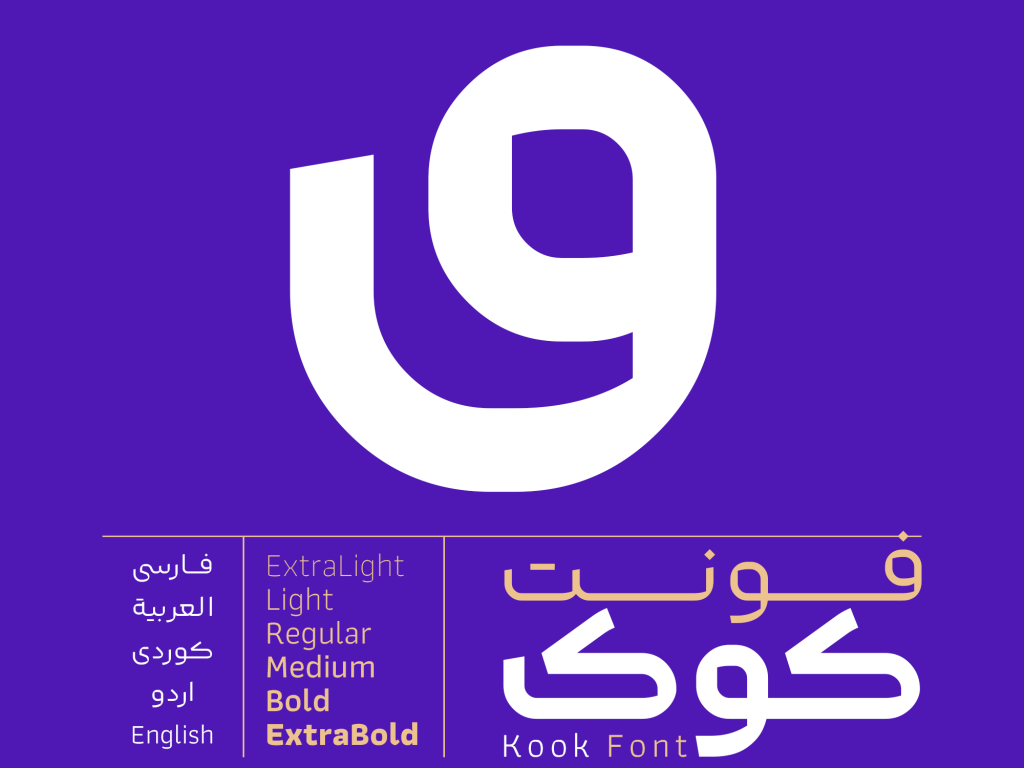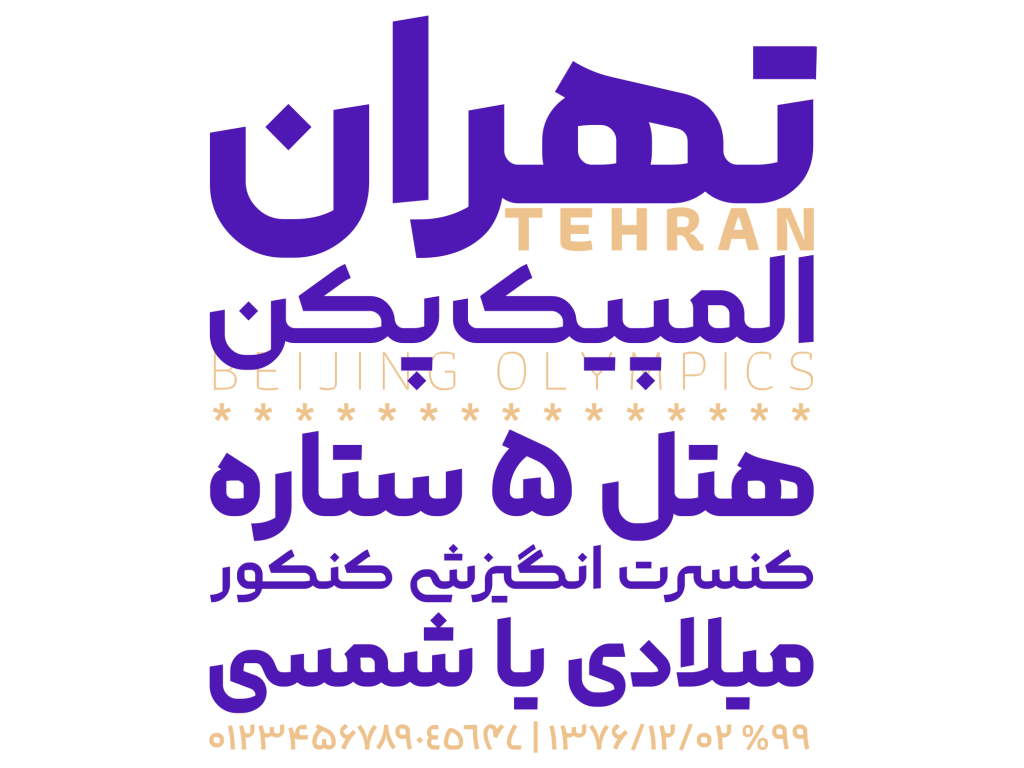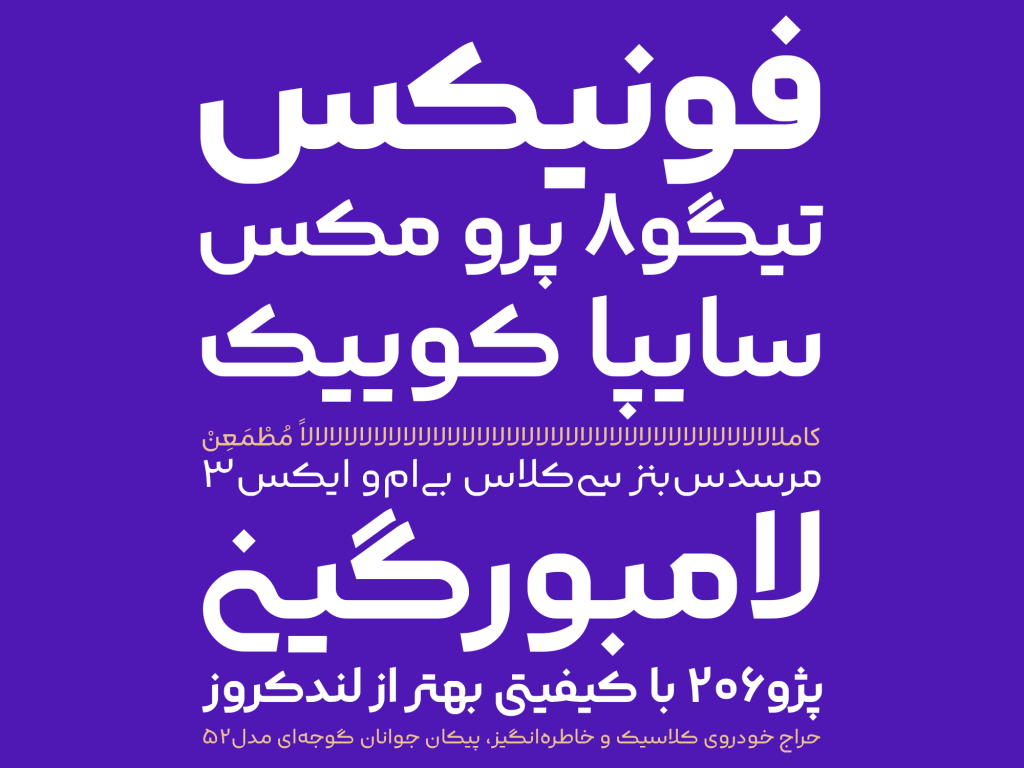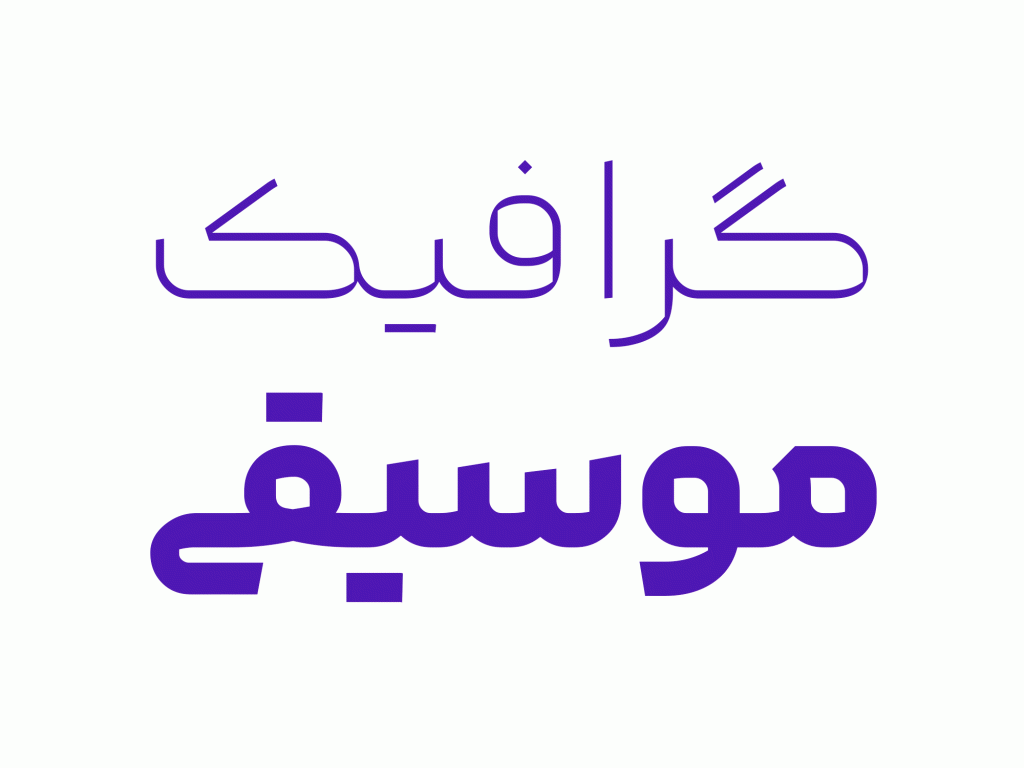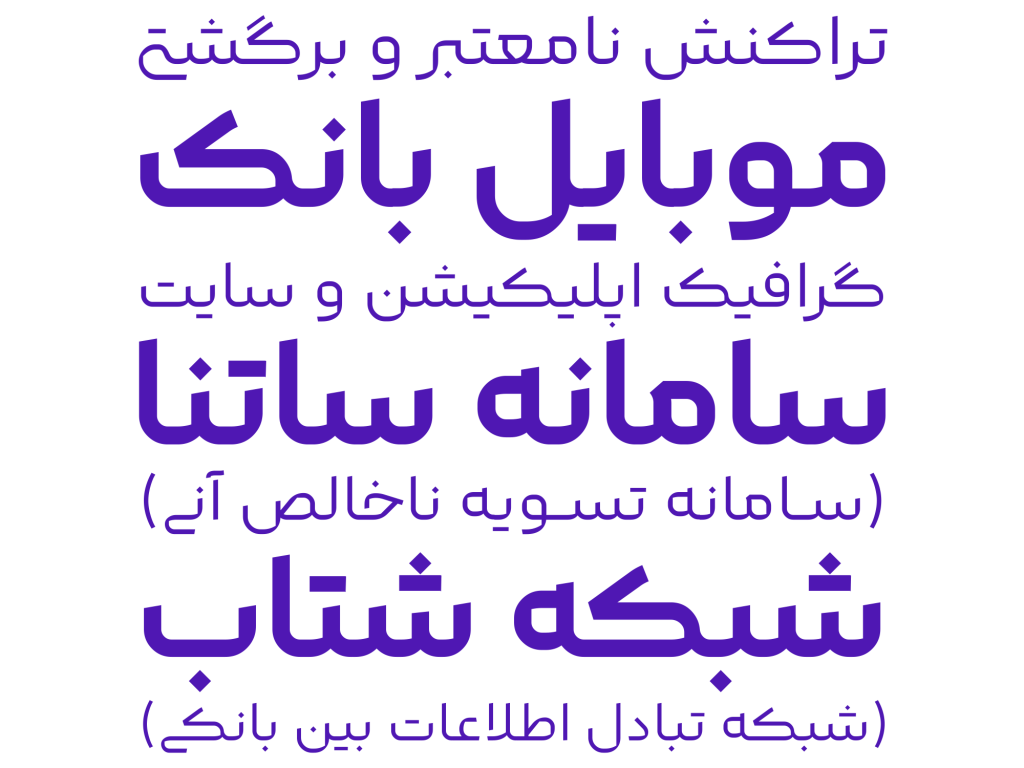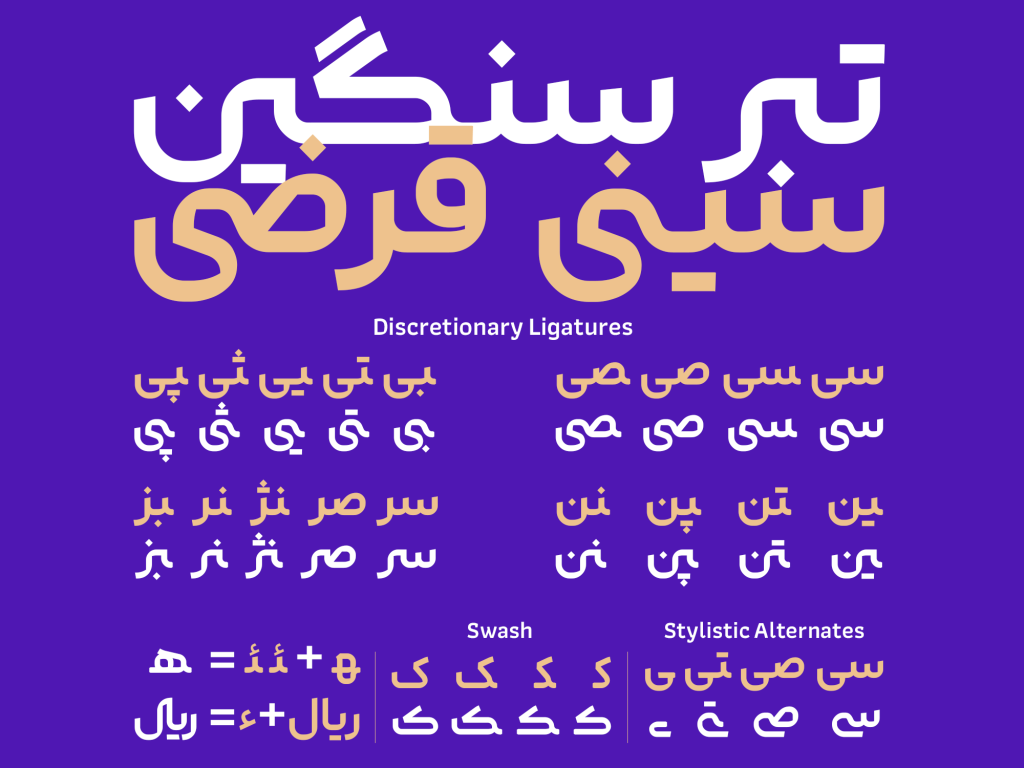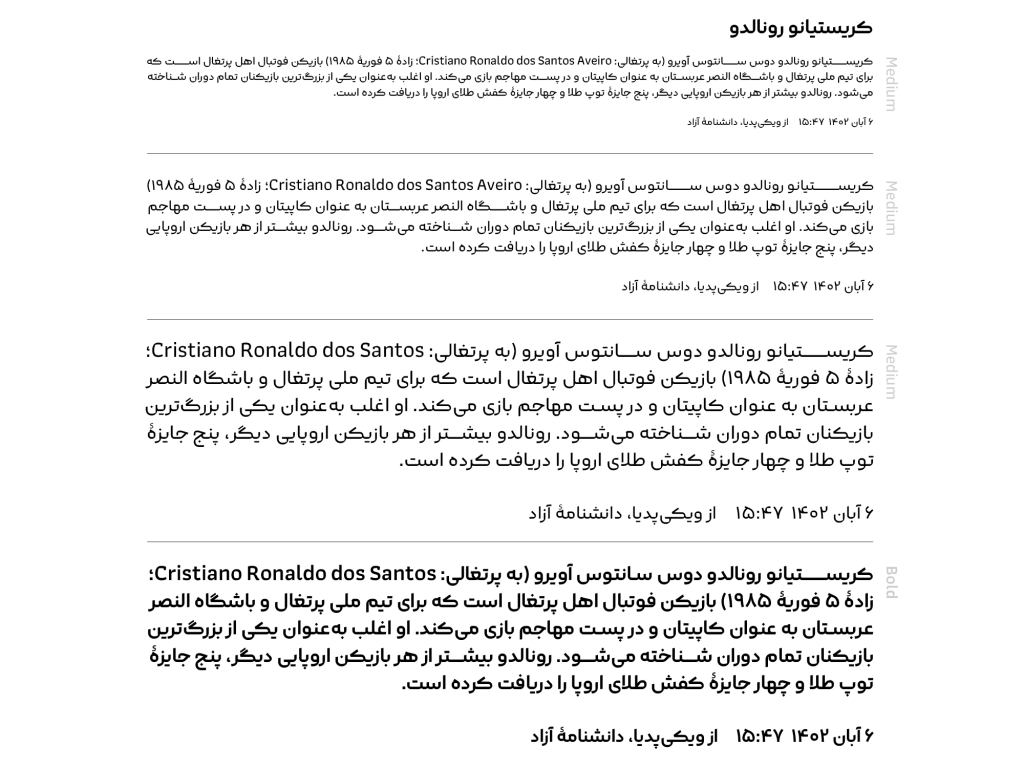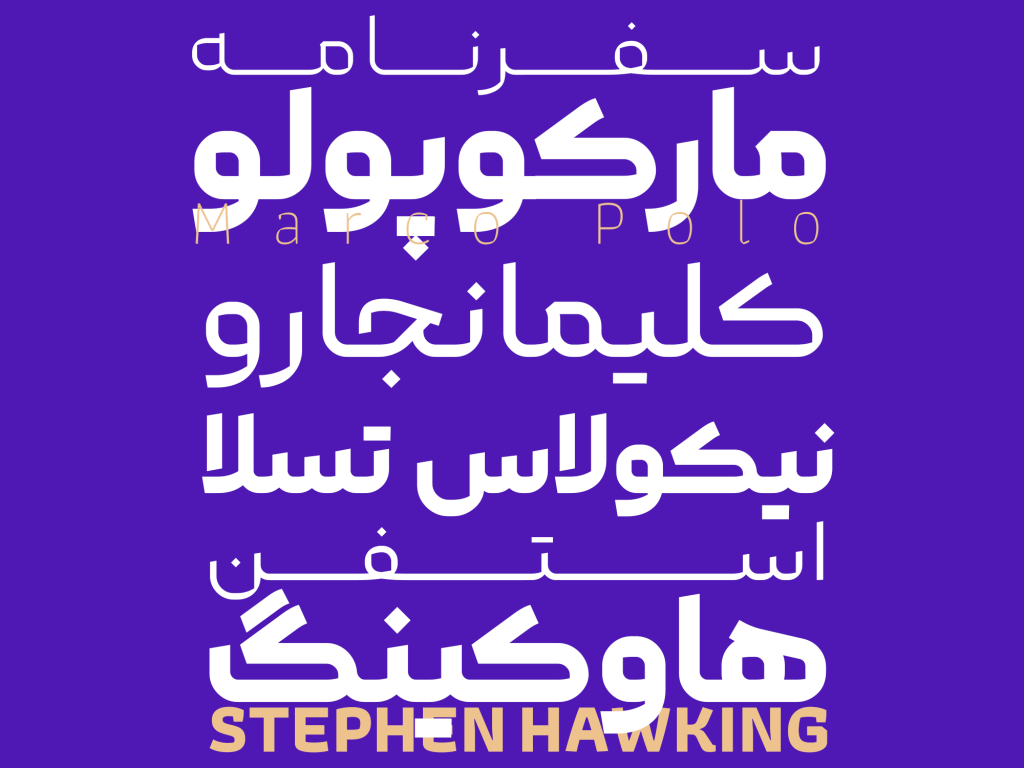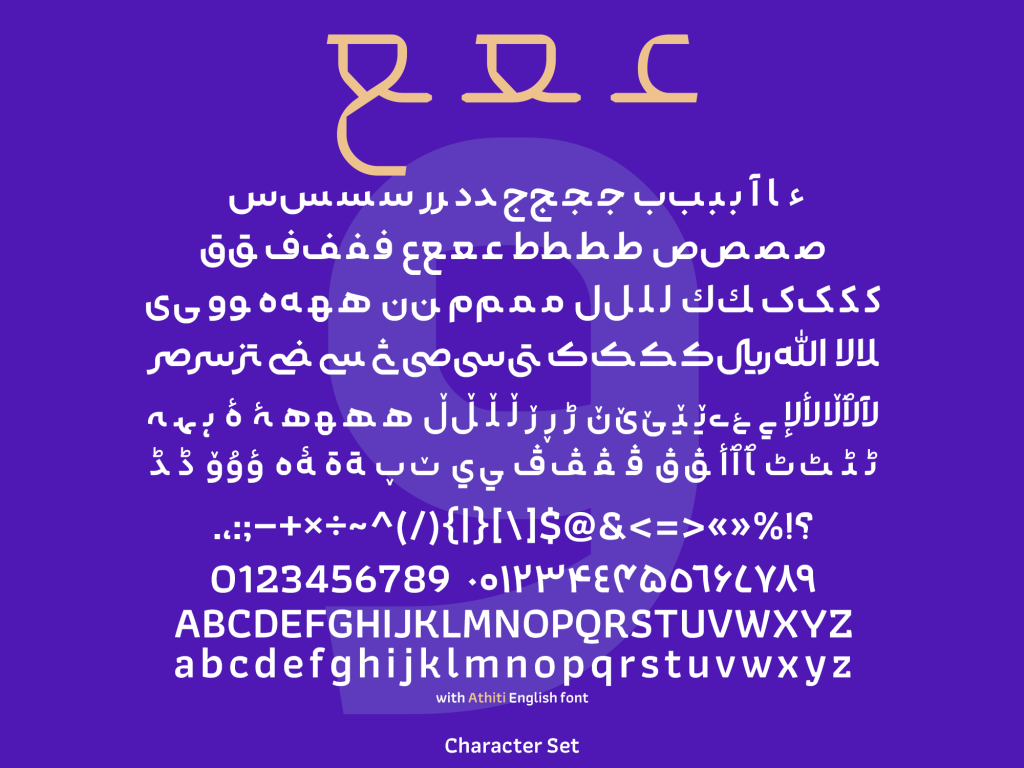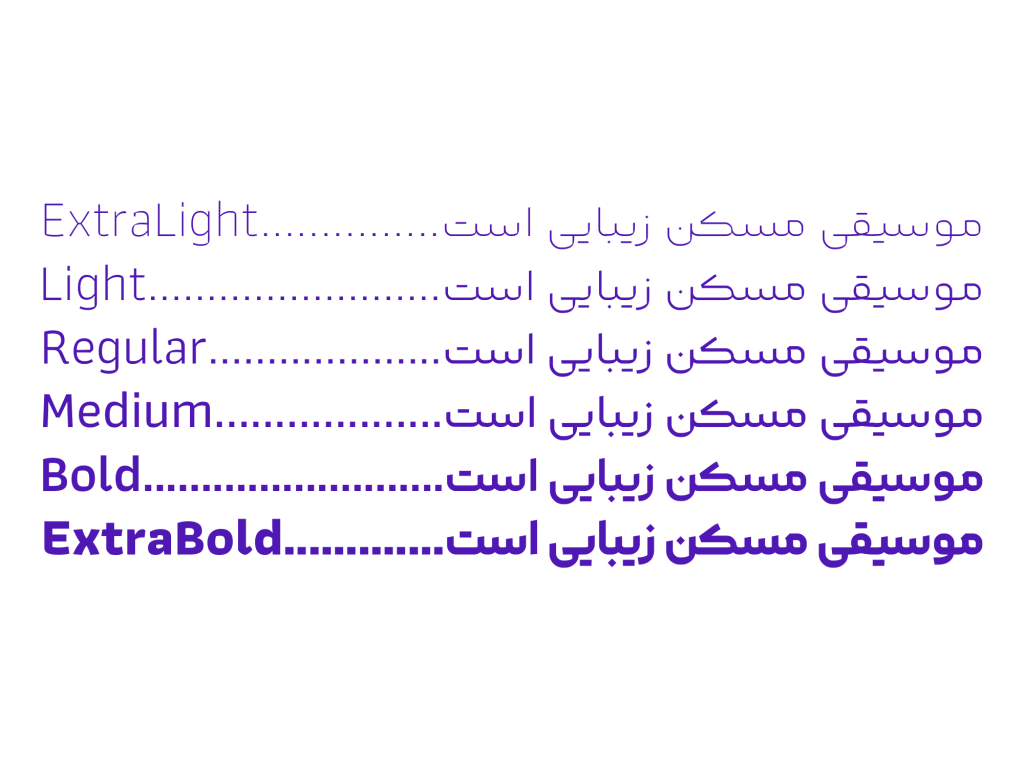
فونت کوک – قلمی از خانواده هندسی
فونت کوک طراحی شده توسط آقای سعید حقیقت از خانواده تایپ فیس های هندسی می باشد. با اندکی دقت در این قلم درمی یابید که بعضی مفصلها دارای شکست و زاویه تند و تیز و خمیدگیهای خارج از قاعده در برخی حروف دیده میشود. همین نکات و تمر کز به ظرافت های ریز و درشت سبب افزایش خوانایی و روان خوانی این قلم شده است.
اگر بخواهیم کاربرد و گستره استفاده از این قلم را معرفی کنیم بی شک مناسب موضوعات معاصر تبلیغاتی، طراحی رابط کاربری و محتوای شبکههای اجتماعی و صفحات وب می باشد. فونت زیبای یکان بخ از نظر شباهت و هم خانوادگی نزدیکی زیادی به این تایپ فیس دارد
مروری بر مسیر پیدایش تا رشد کوک
طراح درباره روند طراحی این قلم میگوید: ” ایده طراحی زمانی به ذهنم رسید که در حال طراحی یک پوستر تبلیغاتی بودم. خواستار فونتی بودم که تلفیقی از خطوط هندسی و خوشنویسی باشد و همچنین همنشینی خوبی با فونتهای لاتین داشته باشد. “
کوک در ابتدای پیدایش خود ساختاری ساده و هندسه ای عاری از پیچیده گی های خاص را در دل خود داشت و اما رفته رفته در مسیر به روز رسانی و رشد خود با اعمال استایل پیچش قلم و چندبار اصلاح و بازبینی به فرم کنونی رسید. تلاش شده است اجزای این فونت با یکدیگر هم خوانی لازم را داشته باشند .
این قلم دارای 6 وزن متفاوت بوده که از زبان فارسی، عربی، کردی، اردو و انگلیسی پشتیبانی میکند. کوک شخصیتی با ثبات و محکم و در عین حال پرانرژی و شاداب دارد. در زیر تصاویری زیبا از این قلم را می توانید مشاهده کنید.
این قلم از زبانهای فارسی، عربی، کردی، اردو و انگلیسی پشتیبانی میکند.